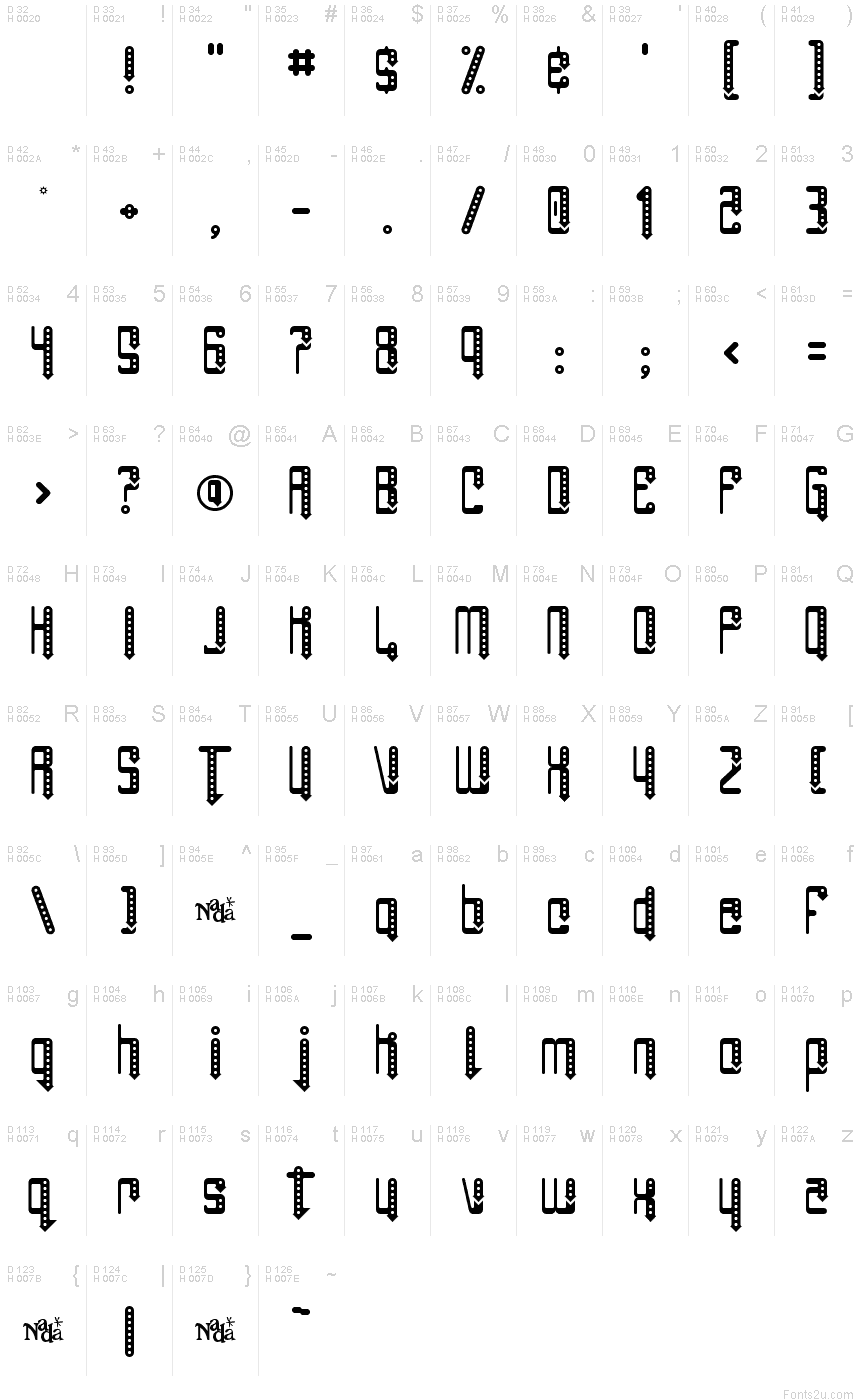
Angie Pierced di R.Gast - GreyWolf WebWorks è un font display decorativo gratuito che trasforma ogni lettera in un segno grafico massiccio e rivettato. Le forme alte e arrotondate sono traforate da audaci "piercing" circolari, mentre alcuni tratti terminano con punte a freccia affilate, conferendo alla famiglia Angie un tocco industriale giocoso. Il risultato sembra un mix tra luci da insegna, borchie di jeans e scritte artigianali ritagliate a mano: accattivante, tattile e leggermente ribelle.
Con Angie Pierced, i titoli e le brevi frasi catturano subito l'attenzione, rendendo questo font gratuito perfetto per poster, inviti a feste, packaging fai-da-te, progetti per bambini, grafiche di giochi e banner per social media originali. Le sue forme dense e dritte funzionano bene nei titoli grandi, dove i fori traforati risaltano davvero. Per il testo principale, abbinalo a un carattere sans serif semplice e pulito, in modo che Angie Pierced possa rimanere sotto i riflettori senza sovraccaricare il layout.